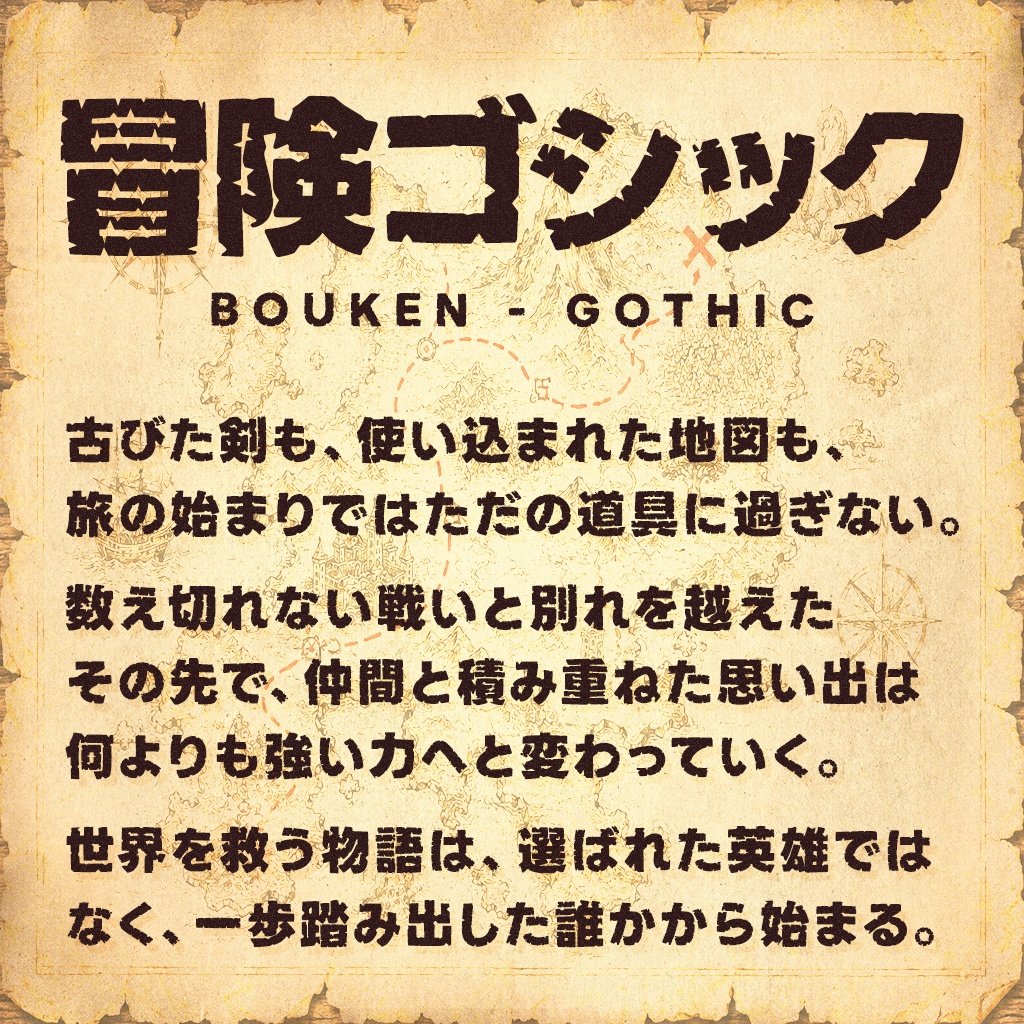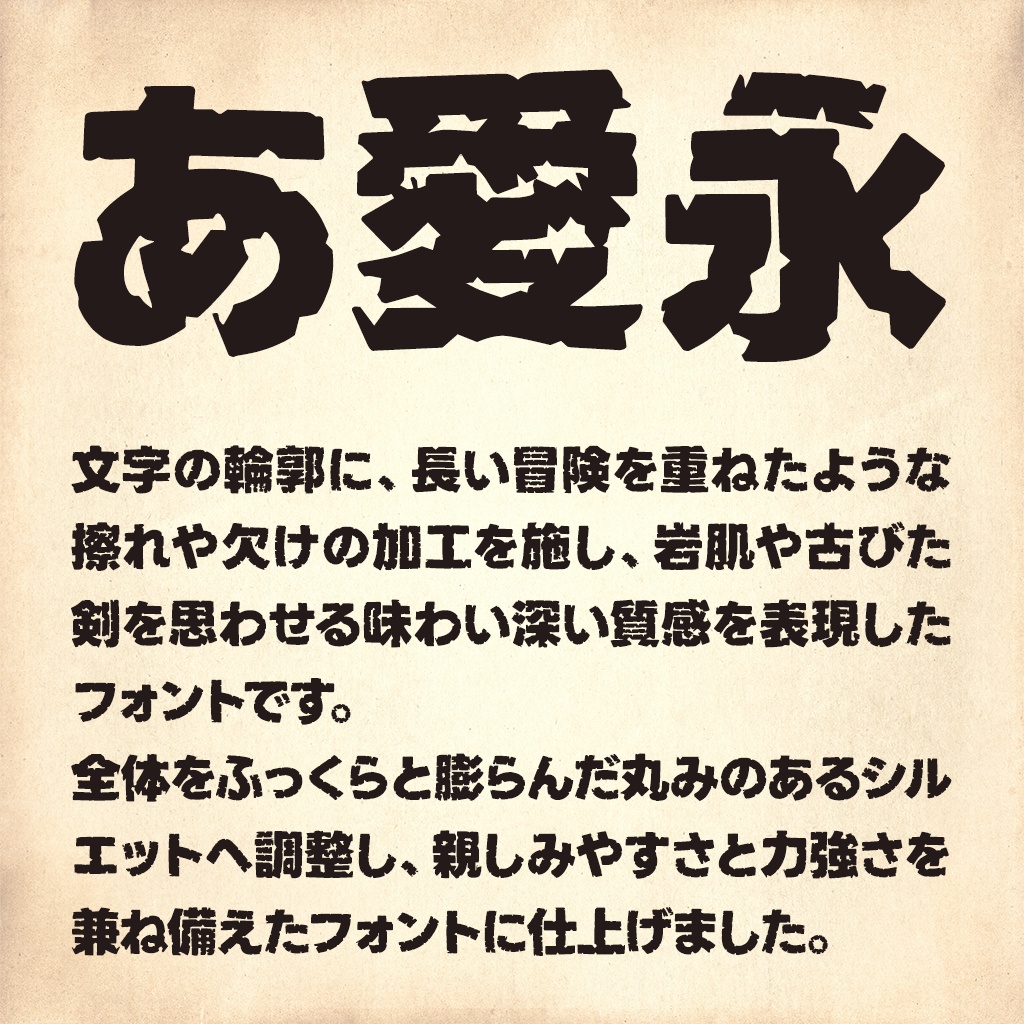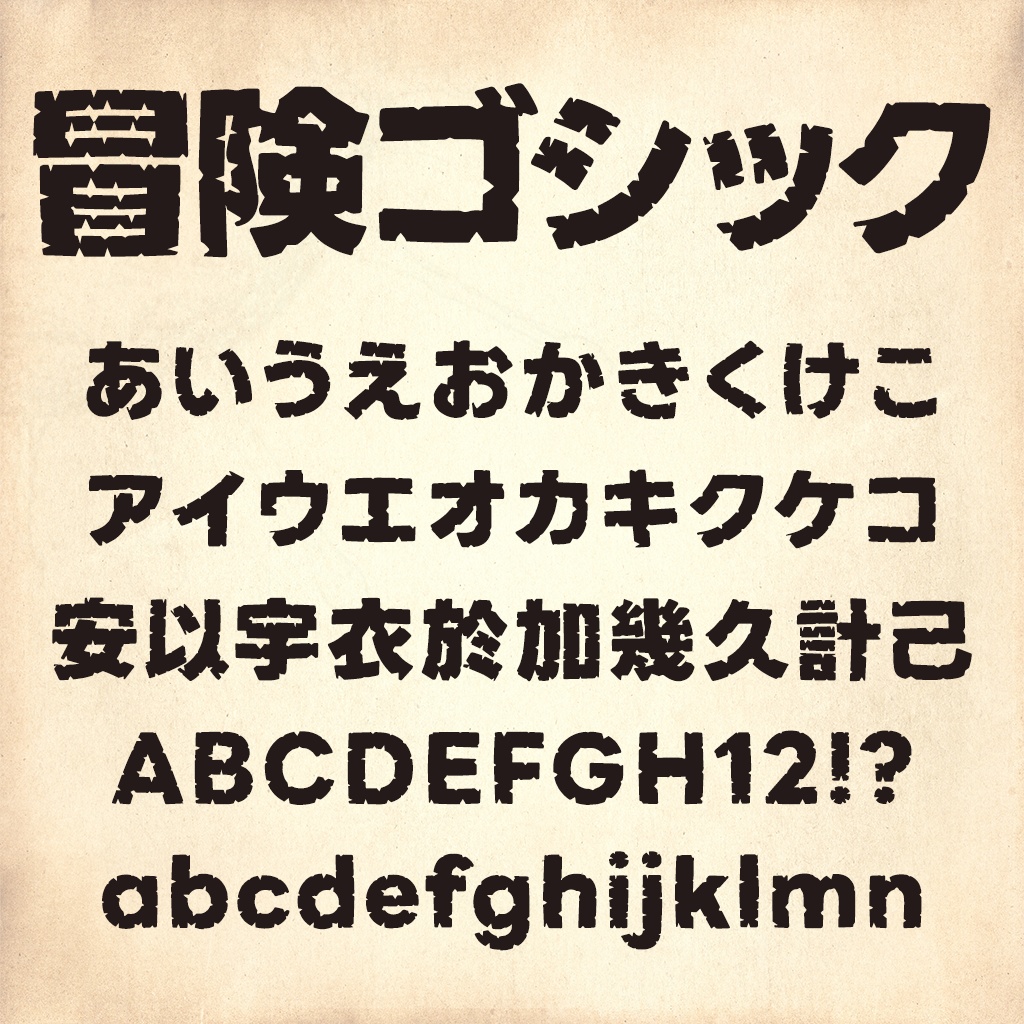
冒険ゴシック(フリーフォント)
【概要】 冒険ゴシックは、LINE Seedをベースに、文字の輪郭には、長い冒険で刻まれた傷跡を思わせるラフ加工や欠け表現を施し、幾度もの試練を乗り越えてきたような力強い質感を表現しました。 また全体をふっくらと膨らんだフォルムへ調整し、親しみやすさと力強さを兼ね備えたフォントに仕上げました。 ファンタジーや冒険譚、RPG作品のタイトルはもちろん、ゲーム実況のサムネイルやイベントロゴなどにもぴったりなフォントです。 無料版と投げ銭版(¥500)のフォント内容は同一です。 【ライセンス・規約について】 このフォントはSIL Open Font License 1.1で公開されています。 個人・商用にかかわらず無償で使用可能で、動画・サムネイル・ゲーム等への組み込みなどご自由にご利用ください。 詳しいSILライセンスについてはサイトをご確認ください。 https://licenses.opensource.jp/OFL-1.1/OFL-1.1.html 当フォントを利用して発生した、いかなる損害についても作者は責任を負いません。 フォントデータをダウンロードした時点で利用規約に同意したものとみなします。 【改変元フォント】 LINE Seed 関係者に深くお礼申し上げます。 【アップデート】 2026/07/14《ver1.000》リリースしました 2026/07/14《ver1.000》一部デバイスでインストールができないバグを修正しました ========= 崩れなどございましたら、お知らせいただけますと幸いです。